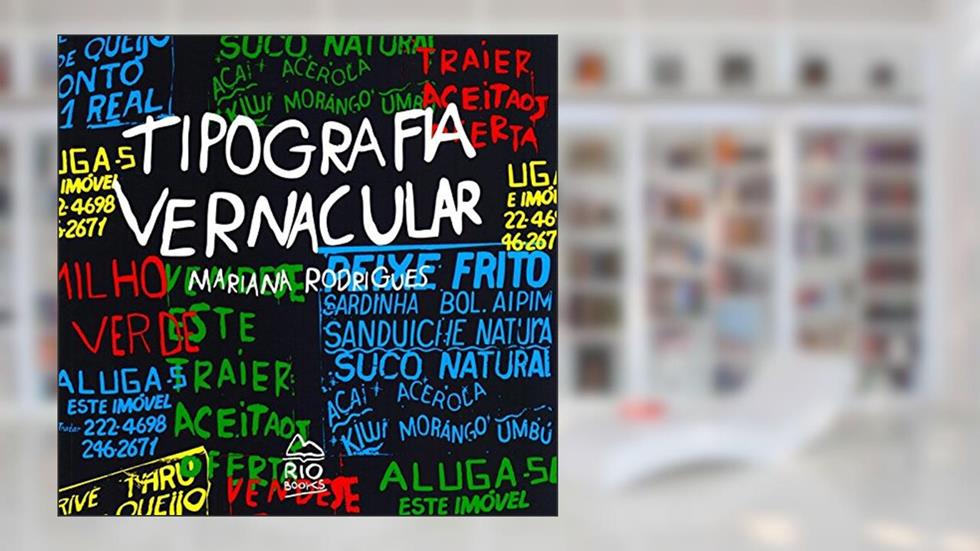
Tipografia Vernacular não é apenas um livro sobre letras; é um convite a uma viagem sensorial pelo universo da comunicação visual que permeia nosso cotidiano. Mariana Rodrigues, com sua caneta afiada e olhar crítico, nos conduz por um labirinto dinâmico de formas e significados, revelando a tipografia que vive nas ruas e nas esquinas, em anúncios, placas e grafites. É um manifesto onde a estética se encontra com a função, uma celebração do que é frequentemente ignorado.
Ao abrir suas páginas, você é imediatamente abraçado por um panorama fascinante: a tipografia não é um elemento acessório; ela é a essência da linguagem visual que molda nossa experiência. Mariana não se limita a descrever as letras; ela explode a ideia de que a tipografia é algo meramente técnico e impessoal, apresentando-a como uma forma de arte viva e pulsante, que conta histórias e expressa culturas. Seu olhar perspicaz transforma o ordinário em extraordinário, fazendo você olhar para o que está à sua volta com um novo olhar - um efeito quase mágico.
Os comentários dos leitores variam entre os que se sentem inspirados a observar o mundo com mais atenção e os que se sentem desafiados a repensar sua própria prática como designers. Há quem critique sua abordagem ao considerá-la excessivamente acadêmica em momentos, mas isso se torna um teste para aqueles que estão prontos para mergulhar no profundo. As vozes que clamam por uma experiência mais prática e acessível se deparam com a magnitude da obra de Mariana, que exige que sejamos mais que meros observadores: somos chamados a nos tornarmos participantes ativos na transformação do ambiente em que vivemos.
E se você ainda hesita, considere isso: o livro não é apenas uma leitura; é uma revolução silenciosa, uma forma de arte que clama por reconhecimento e respeito. Os estilos tipográficos que encontramos em nossas cidades são reflexos de nossas identidades, histórias e lutas. Cada letra, cada sinal, cada forma desenhada nas calçadas é um fragmento de nossa cultura e sociedade.
O que Mariana Rodrigues faz aqui é, de certa forma, um ato de resistência contra a homogeneização cultural. Em tempos em que as letras se tornam cada vez mais digitais e soubermos menos sobre suas origens, Tipografia Vernacular ressuscita a importância de valorizar o que é local, o que é genuíno. Não se trata apenas de ler; trata-se de ver, sentir e entender a força que cada forma escrita pode ter.
Se você ainda não se deixou envolver, está na hora de se perder nessas páginas e descobrir o poder que uma tipografia vernacular pode ter em sua vida e no seu entorno. Não se engane: este não é só um livro para designers, mas um legado para qualquer um que deseje ver e sentir mais intensamente o mundo à sua volta.